6개월에 걸친 「늦봄」 제작 과정의 이야기
「Sandoll 늦봄」은 본문용 2종(Light, Medium)과 제목용 2종(White, Black)으로 구성된 폰트인데요. 산돌에서 오랜만에 출시했던 본문용 폰트이면서 보기 드문 명조 계열 폰트입니다.
「늦봄」은 당시 각각 5년차, 4년차를 맞이한 폰트 디자이너 2명이 개발했습니다. 본문용 폰트와 제목용 폰트를 동시에 개발한 것은 새로운 도전이었지만, 마침내 ‘감성 명조’라는 결과물을 완성할 수 있었는데요. 6개월에 걸친 「늦봄」 제작 과정의 이야기를 들어봤습니다.
박지인, 구모아 폰트 디자이너
Q. 기존의 본문용 폰트와는 다른, 새로운 명조 폰트라고 하니 기대가 되는데요. 「늦봄」에 대한 소개를 부탁드려요.
구모아 디자이너(이하 모아) : 「늦봄」은 붓글씨를 모티브로 한 명조 계열의 폰트로(휴머니스트 세미 세리프), 새로운 분위기의 본문용 폰트를 제작해보자는 생각에서 시작하였습니다.
현대의 명조체는 해서체라는 서예의 필법에서 영향을 받아 발전해왔는데요. 부리와 맺음, 빗침 등의 명조의 특징이 되는 형태는 ‘붓’이라는 모필 도구의 흔적에서 유래한 것입니다. 그런데 붓의 표현이 너무 정리되면서 오히려 모필이 가진 원래의 감성을 느끼기 어려운 형태가 되었어요.
전해 내려오는 고서를 살펴보아도, 화선지에는 붓으로 썻으나 인쇄를 위해 목판으로 깍아내 찍은 것이라서 이 역시 모필의 흔적을 감상하기에는 어려움이 있었습니다. 이를 배경으로 「늦봄」은 전통적인 모필의 감성을 다시 살릴 수 있는 폰트를 개발하고자 했던 것이 주요한 컨셉이었고, 가장 큰 매력 요소이기도 합니다.
「늦봄」의 컨셉 이미지
Q. 모필(붓글씨)을 모티브로 하고 있다고 하셨는데요. 어떤 것들을 중심으로 작업하셨나요?
A. 모아 : 일단은 붓글씨의 여유 있는 모습을 보여주고 싶었습니다. 자간을 비교적 넉넉하게 잡아주고, 시각적으로 흰 공간을 넓게 감싸도록 자소의 높낮이를 다양하게 해주었습니다.
Q. 「늦봄」이라는 폰트 이름도 참 잘어울리는 것 같아요.
A. 모아 : 「늦봄」의 이름은 시안 문구에서 따왔습니다. 감성적인 명조가 컨셉이어서, 시안 문구에도 애절한 감성이 묻어났으면 했습니다. 그떄 채택되었던 것이 김윤아의 노래 ‘야상곡'에 나오는 ’꽃잎 흩날리던 늦봄의 밤'이라는 문장이었습니다.
처음부터 폰트 이름으로 삼았던 것은 아니었고 프로젝트 가칭으로 편하게 불렀었는데, 컨셉과 ‘늦봄’이란 이름이 자연스럽게 이어지더라고요. 늦었지만 천천히 꽃 피웠으면 하는 바람을 담아 최종적으로 「늦봄」으로 결정하게 되었습니다.
Q. 「늦봄」을 작업하면서 떠올렸던 이미지나 문장이 더 있을까요?
A. 모아 : 시안의 문구가 된 야상곡의 가사를 많이 생각했습니다. 그외에도 사랑과 관련한 시도 많이 떠올렸는데요. 새벽 2시의 촉촉하고 서정적인 감성들을 많이 생각하며 작업했습니다.
바람이 부는 것은 더운 내 맘 삭여 주려
계월이 다 가도록 나는 그저 애만 태우네
꽃잎 흩날리던 늦봄의 밤
아직 남은 님의 향기
이제 오시려나, 나는 애만 태우네.
애달피 지는 저 꽃잎처럼
속절없는 늦봄의 밤
…
김윤아 <야상곡> 중에서
우린 오래오래 안녕이지만
오래오래 사랑한 기분이든다
네 머리를 쓰다듬고 강에 뛰어들고 싶다
오래오래 허우적거리며 손의 감촉을
버리고 싶다
한 행성이 내게 멀어져 간 것은 재앙이다
네가 두고 간 것들을 나만 보게 되었다
너를 뭐라 불러야할지 모르겠다
성동혁 <1226456> 전문
Q. 「늦봄」은 본문용 2종(Light, Medium)과 제목용 2종(White, Black)이 동시에 개발되었는데요. 두 분이서 어떻게 작업을 나누어 진행하셨나요?
A. 박지인 폰트 디자이너(이하 지인) : 「늦봄」은 뼈대에 해당하는 Light와 white가 먼저 개발되었습니다. 그런 다음 변형되는 Medium과 Black의 개발로 넘어갔는데요. 모아 매니저님이 이 과정을 진행해주셨고, 제목용 Black에 대한 가이드를 주어 제가 Black 디자인에 참여했습니다.
A. 모아 : 「늦봄」 기획 당시 본문용 2종과 제목용 2종에 대한 어느 정도 틀을 잡아 놓았는데요. 스케치를 잡아 놓은 상태에서 본문용을 제작하면서 지인씨가 제목용 Black 디자인에 참여하게된 형태였습니다.
Q. 폰트를 두 사람이 함께 개발하면서 어려운 점도 있을 것 같습니다. 어떠셨나요?
A. 지인 : 「늦봄」 은 직선보다 곡선이 훨씬 많았는데요. 그런 부분들을 이해하고 같은 규칙으로 만들었을 때 전체적으로 같은 분위기를 낼 수 있게 됩니다. 그래서 포인트와 핸들의 규칙이 서로 공유되어야 한다고 생각했어요. 그 안에서 공간이나 균형도 봐야하고 한 글자를 만드는데 생각해야 할 것들이 많았습니다.
무엇보다 혼자 하는 작업이 아니기 때문에 파일을 관리하는 것도 쉽지 않았습니다. 파일이 몇 차례 왔다 갔다 하다 보니, 이 파일이 수정된 파일인지 아닌지 구분도 잘 해야 했거든요.
Q. 폰트의 통일성을 맞추기 위해서 어떤 작업들이 필요할까요?
A. 모아 : 통일성을 위한 작업은 다양하지만, 앞서 말한 곡선 외에도 「늦봄」은 전체 패밀리의 글자 구조를 통일하는 작업을 거쳤습니다. Light가 기준이 되어 Medium, white, Black이 각각의 형태에 맞게 조금씩 수정되었습니다.
구조가 같다는 것을 'ㄱ'으로 예로 들어 설명하자면, 가로줄기와 연결되는 빗침을 그릴 때, 그 안을 관통하는 뼈대가 있고요(white), 뼈대를 중심으로 살이 붙는 형식이라고 보시면 됩니다. Black의 경우는 거기서 개성이나 포인트가 될 수 있는 부리와 꺾임, 맺음의 요소를 획의 콘트라스트와 함께 극대화하여 표현한 형태라고 할 수 있습니다.
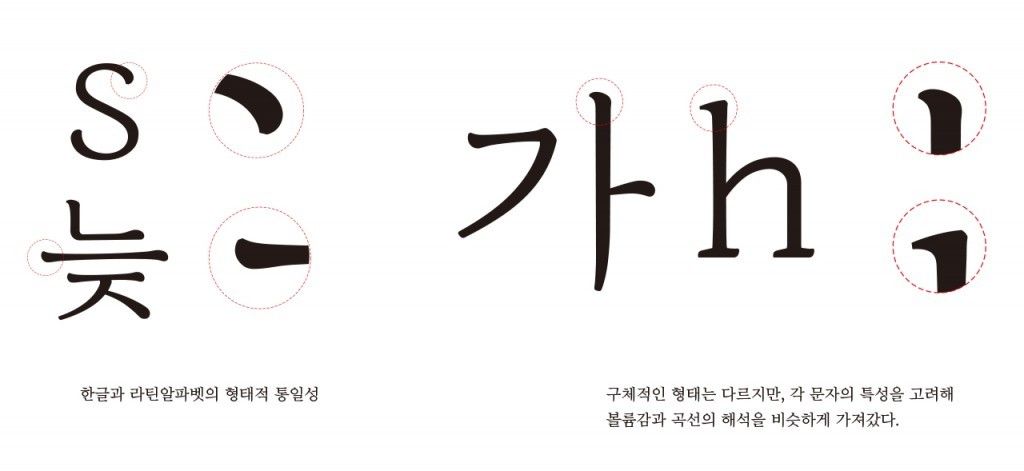
Q. 제목용으로 개발된 white는 굉장히 가는 두께로 디자인되었는데요. 일반적으로 제목용 폰트라고 하면 두꺼운 디자인을 많이들 떠올리잖아요.
A. 모아 : 제목용은 말 그대로 제목에 쓰였을 때 어울리는 형태를 말합니다. white처럼 가는 폰트는 작게 썼을 때는 잘 보이지 않고, 크게 썼을 때는 잘 보일 수 있기 때문에 제목용이라고 할 수 있어요. Black처럼 굵은 글자는 회색도가 높기 때문에 눈에 잘 띄게 되고, 역으로 White처럼 가는 폰트는 선 밖으로 공간을 많이 감싸줄 수 있기 때문에 더욱 선명하게 인식합니다. 이러한 이유로 가는 폰트들이 제목용으로 사용되고는 합니다.
A. 지인 : 제가 제작했던 「Sandoll 푸른밤」는 아주 가는 형태의 헤어라인 폰트인데요. 이 역시 헤드라인으로 구분합니다. 「Sandoll 고딕Neo1」도 패밀리 양 끝에 Thin과 Heavy를 제목용으로 구분되는 것도 같은 이유입니다.
A. 모아 : White는 가늘기 때문에 작게 쓰면 아예 안 보일 수 있어요. 최소한 16pt 이상에서 사용해야 예쁘고 잘 보입니다. 이러한 제목용의 용도를 더 분명하게 하기 위해 의도적으로 더욱 가늘게 제작했습니다.
대표적인 가는 디자인의 제목용 폰트 「Sandoll 하이테크」, 「Sandoll 푸른밤」
Q. 「늦봄」 의 패밀리 중에서 가장 인상적인 폰트는 Black이 아닐까 싶어요.
A. 지인 : Black은 상당히 개성 있는 폰트입니다. 일단 딱 보기에 획 대비도 크고 강한 느낌을 주니까요. 한 글자씩 보다 보면 부드러운 곡선들로 이루어져있어 생각보다 굴곡이 많은데, 그 곡선으로 인해서 표현될 수 있는 개성들을 살리는데 최대한 집중해서 작업했습니다.
A. 모아 : Black은 말하자면 매우 ‘센’ 느낌의 폰트입니다. 형태도 분명하고 획도 굵어서 아주 강하게 느끼실 수도 있습니다. 처음에 시안을 작업할 때는 강하면서 곡선이 두드러져서 화려해 보였으면 했어요. 화려한 꽃이 어우러진 봄의 느낌을 블랙이 보여줄 수 있길 바랬습니다. 거기까지 전달이 되었는지는 잘 모르겠네요. (웃음)
Q. 「늦봄」은 붓글씨를 모티브로 한 폰트라고 말씀해주셨는데, 붓글씨의 활자화에 대해서 설명해주시면 좋을 것 같습니다.
A. 모아 : 붓으로 글을 쓰고, 활자화하여 인쇄를 하는 과정을 생각해보면 이해가 쉽습니다. 인쇄하기 위해서는 (금속 또는 목판 등) 판이 필요하게 되고 이 판에 활자를 ‘새기게’ 됩니다. 깎는다고 표현하죠. 과거에는 인쇄의 정교함이 지금과 같지 않았기 때문에 끝을 각지게 깎아낸다고 하더라도 끝이 뭉그러져서 표현되는 일이 많았습니다. 그런 이유로 선명한 인쇄를 위해 더욱 끝을 날카롭게 깎아줄 필요가 있었어요. 그래서 폰트를 위한 도안을 제작 할 때도 역시 우리가 익숙하고 본래 가지고 있던 쓰기 방식인 붓글씨를 모티브로 하지만, 인쇄 환경을 고려하여 직선위주로 정리가 된 것이 아닌가 하는 생각이 들어요.
하지만 현대의 인쇄 기술은 그 당시와는 비교도 할 수 없을 만큼 발전되었기 때문에 어떻게 그린다고 하더라도 정교하게 인쇄하는 것이 가능해졌습니다. 원하는 모양으로 그릴 수 있게 되었죠.
인쇄 기술의 발전으로 보다 정교한 표현이 가능해졌다
Q. 이야기를 들어보니 붓글씨를 모티브로 폰트를 제작하기 위해서도 많은 연구들이 있었을 것 같아요.
A. 모아 : 「늦봄」 작업 전부터 붓 형태 자체에 대한 생각을 더 많이 했어요. 붓으로 글씨를 많이 써보고 관련자료들도 많이 찾아봤습니다. 제가 서예를 조금 쓸 수는 있지만, 붓의 흐름과 균형에 대해 컨셉과 방향을 분명히 하기 위해 많은 책과 논문들을 참고했습니다.
「늦봄」의 경우 손으로 썼지만 사용성을 위해 잘 정리된 활자의 인상도 담기길 바랬어요. 그럴려면 형태들이 계획적으로 잘 정리가 되어야 했습니다. 하지만 모필이라는 부드러운 필기도구는 획의 마무리와 진행 방향 등의 변수가 너무 많더라고요. 한정된 시간 동안 계속 연구하기 어려워 필기구의 느낌을 잘 살려낸 폰트들도 많이 찾아봤습니다.
일단 비슷한 필기문화를 가진 중국과 일본의 폰트, 펜과 첨필의 형태를 잘 볼 수 있는 라틴 알파벳 문화권과 아랍언어권의 폰트를 참고했습니다. 요즘 발표된 한글 명조 계열 폰트도 많은 도움이 되었습니다. 요즘에는 과거의 폰트나 필사본을 모티브로 작업한 결과물이 많이 보이는데요. 「늦봄」도 그런 시도로 보시면 됩니다.
Q. 폰트를 직접 개발한 디자이너가 생각한 활용처가 궁금합니다. 「늦봄」은 어디에 사용하면 좋을까요?
A. 모아 : 시집, 시집 전체가 늦봄 폰트로 나왔으면 좋겠다는 생각을 해봅니다. 너무 보고 싶어요. 시집에 쓰였을 때의 전체적인 톤도 궁금하고요. 실제 사용자 분들이 어떻게 사용할까 기대가 됩니다.
Q. 마지막 질문입니다. 늦봄을 제작하면서 지향점이 있다면 무엇이었나요?
A. 모아 : 개인적으로 명조 계열의 폰트를 좋아합니다. 명조 디자인에서 다양한 시도를 하는 것도 좋아해요. 앞으로도 이런 방식의 시도들이 많이 있었으면 좋겠고, 「늦봄」이 그 초석이 되었으면 하는 바람이 있습니다. 고딕을 변형 시킨 폰트들은 무수히 많지만 명조를 활용한 폰트들은 많지 않습니다. 아무래도 고려할 사항들이 많다 보니 진입 장벽이 높다고 생각하는 것 같아요. 늦봄을 시작으로 명조를 활용한 재미 있는 디자인들이 많이 나왔으면 좋겠습니다. 늦봄이 그러한 활성화에 일조하길 기대해 봅니다.